为您讲述“楷书来历与楷书起源来由”,楷书又称正书,或称真书。其特点是:形体方正,笔画平直,可作楷模,故名。始于东汉。楷书的名家很多,如“欧体”(欧阳询)、“虞体”(虞世南)、“颜体”(颜真卿)、“柳体”(柳公权)、“赵体”(赵盂附)等。
宋宣和书谱:“汉初有王次仲者,始以隶字作楷书”认为楷书是由古隶演变而成的。据传:“孔子墓上,子贡植的一株楷树,枝干挺直而不屈曲。”楷书本笔画简爽,必须如楷树之枝干也。
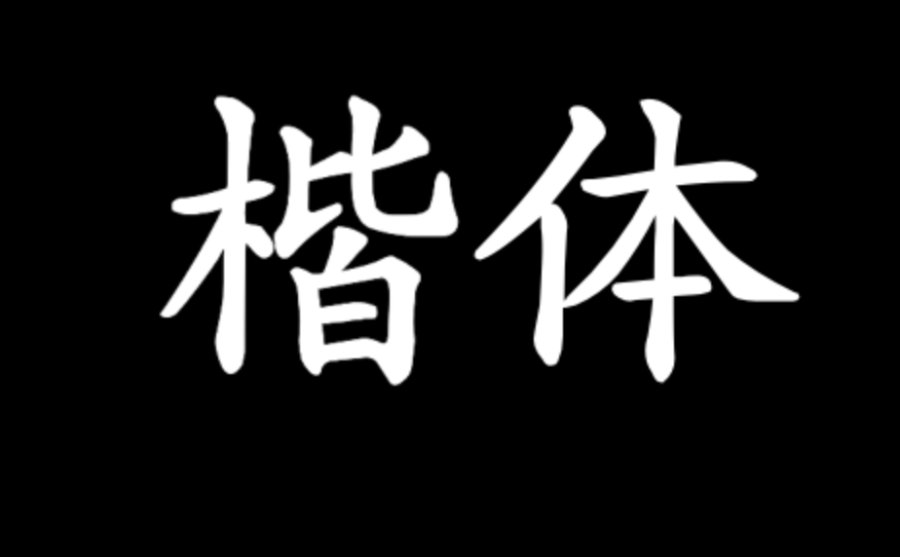
初期“楷书”,仍残留极少的隶笔,结体略宽,横画长而直画短,在传世的魏晋帖中,如锺繇的《宣示表》(左图)、《荐季直表》、王羲之的《乐毅论》《黄庭经》等,可为代表作。观其特点,诚如翁方纲所说:“变隶书之波画,加以点啄挑,仍存古隶之横直”。
东晋以后,南北分裂,书法亦分为南北两派。北派书体,带著汉隶的遗型,笔法古拙劲正,而风格质朴方严,长于榜书,这就是所说的魏碑。南派书法,多疏放妍妙,长于尺牍。南北朝,因为地域差别,个人习性、书风迥然不同。北书刚强,南书蕴藉,各臻其妙,无分上下,而包世臣与康有为,却极力推崇两朝书,尤重北魏碑体。康氏举十美,以强调魏碑的优点。
唐代的楷书,亦如唐代国势的兴盛局面,真所谓空前。书体成熟,书家辈出,在楷书方面,唐初的虞世南、欧阳询、褚遂良、中唐的颜真卿、晚唐的柳公权,其楷书作品均为后世所重,奉为习字的模范。
古人学书法有这一种说法:“学书须先楷法,作字必先大字。大字以颜为法,中楷以欧为法,中楷既熟,然后敛为小楷,以锺王为法”。然根据多年实验研究结果表明:初学写字,不宜先学太大的字,中楷比较适合。
初唐三大书法家,欧阳询、虞世南、褚遂良的楷书,都最适宜作中楷的临摹范本。兹分别简介如后:
欧阳询的正楷,源出古隶,以二王体为基础,参以六朝北派书风,结体特异,独创一格,权威尤炽,其势力深入社会,几为学书的标准本。究其楷书特点,用笔刚劲峻拔,笔画方润整齐,结体开朗爽健。他的楷书碑帖代表作有《九成宫醴泉铭》、《化度寺碑》碑等。
虞世南的楷书,婉雅秀逸,上承智永禅师的遗轨,为王派的嫡系。虽源出魏晋,但其外柔内刚,沉厚安详之韵,却一扫魏晋书风之怯懦。其楷书代表作,当以《夫子庙堂碑》为最。
褚遂良的楷书,以疏瘦劲练见称,虽祖右军,而能得其媚趣。其字体结构看似非常奔放,却能巧妙的调和着静谧的风格,开创了前人所未到的境地,其楷书代表作,当以《雁塔圣教序》为最。